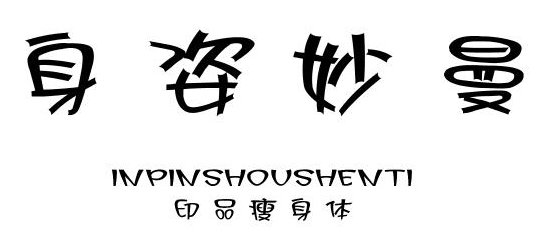
印品瘦身體是義啟字體全新上線的一款一鍵生成的字體,給字體不一樣的特色處理,圓潤(rùn)有型、別致可愛(ài),上寬下窄的二次元風(fēng)格,充滿了減肥般的樂(lè)趣,喜歡的朋友就來(lái)綠色資源網(wǎng)下載吧!
印品首款一鍵生成的字體,得到義啟公司的授權(quán),將其萌妹體字庫(kù)通過(guò)魚(yú)眼特效扭曲處理,借助軟件自動(dòng)生成實(shí)現(xiàn)整體風(fēng)格和諧統(tǒng)一,把原有字體做了瘦身,意在追求個(gè)性大膽嘗試創(chuàng)新的理念。
印品瘦身體是印品系列的首款字體,身姿妙曼整體和諧,給人靈動(dòng)脫俗的視覺(jué)美感,可以廣泛運(yùn)用在平面設(shè)計(jì)、包裝設(shè)計(jì)等趣味主題上。